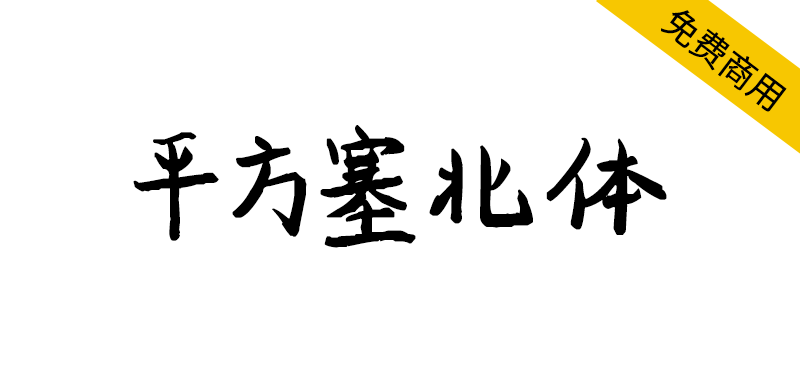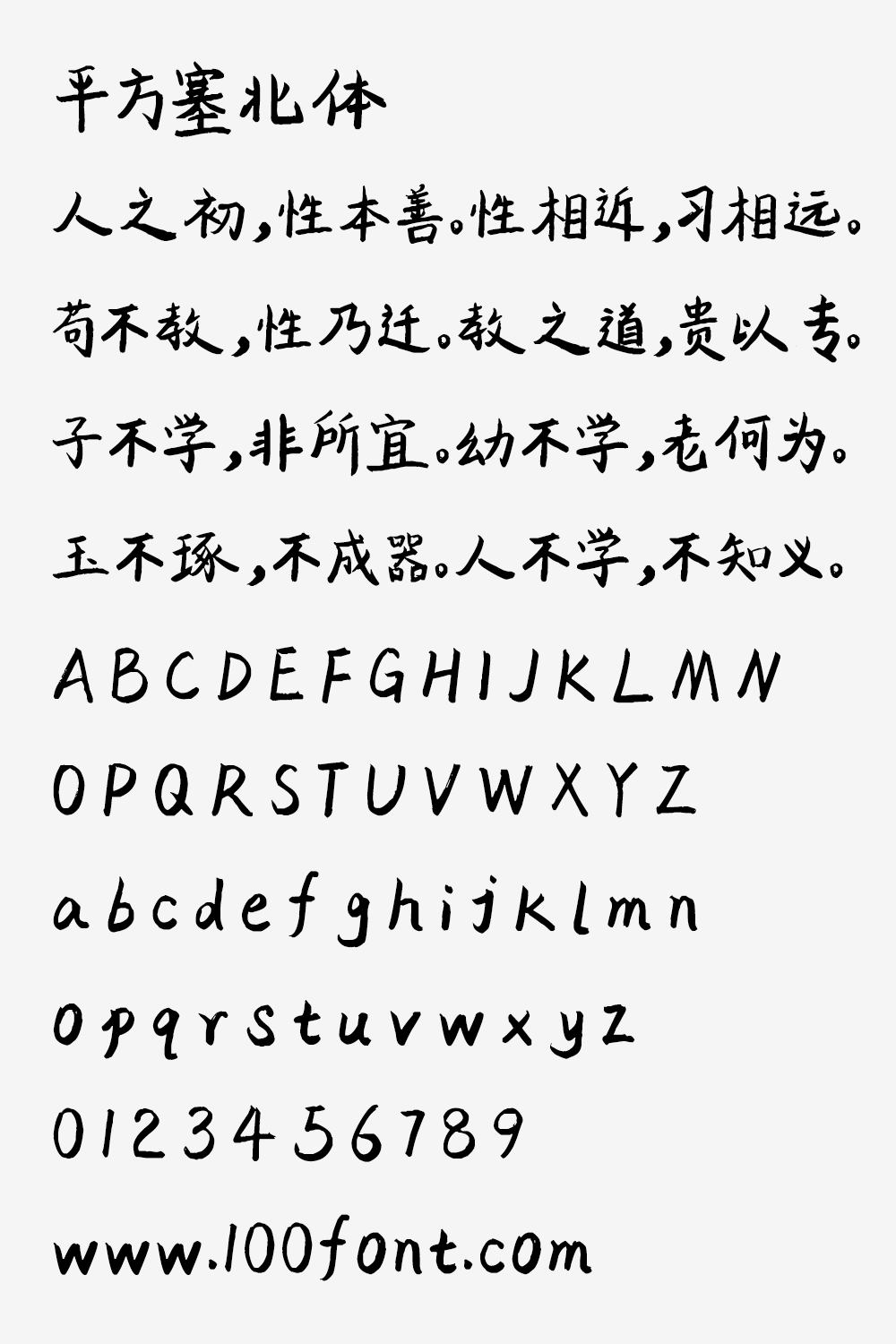
【平方塞北体】一款粗犷有力、浑厚沉稳的手写体字体
发现一款宝藏字体!平方塞北体,以其粗犷有力的线条和浑厚沉稳的笔触,为你的设计注入强烈的视觉张力。无论是产品包装还是游戏标题,它都能完美驾驭。更重要的是,这款极具风格的手写体允许个人和企业免费商用!立即解锁这款能让你的作品脱颖而出的设计利器。
【平方塞北体】一款粗犷有力、浑厚沉稳的手写体字体
平方塞北体是一款线条粗犷有力、笔触浑厚沉稳的手写风格字体,整体呈现强烈的视觉张力,适用于印刷制品、产品包装、影视游戏、标题设计等设计场景。
【平方塞北体】一款粗犷有力、浑厚沉稳的手写体字体